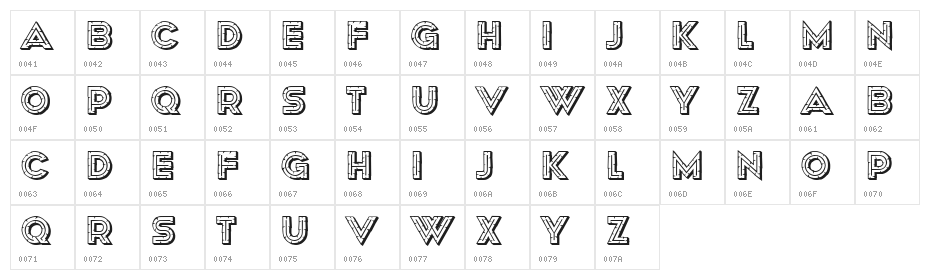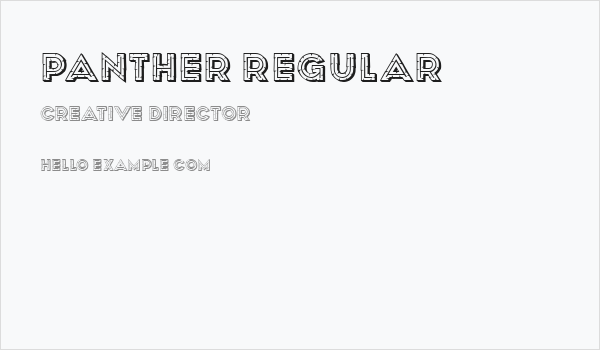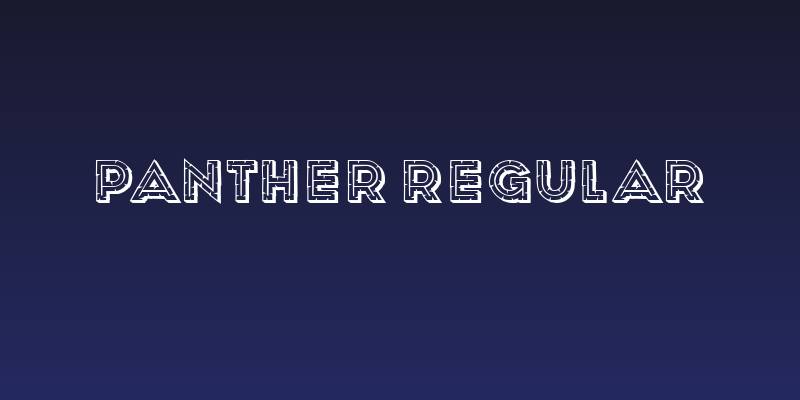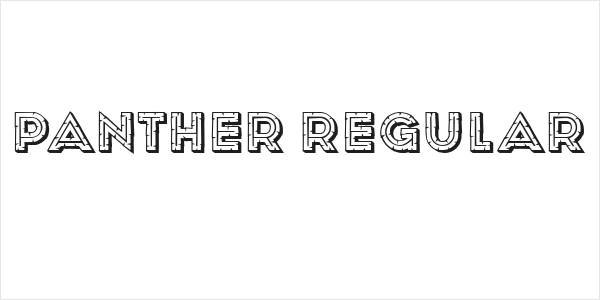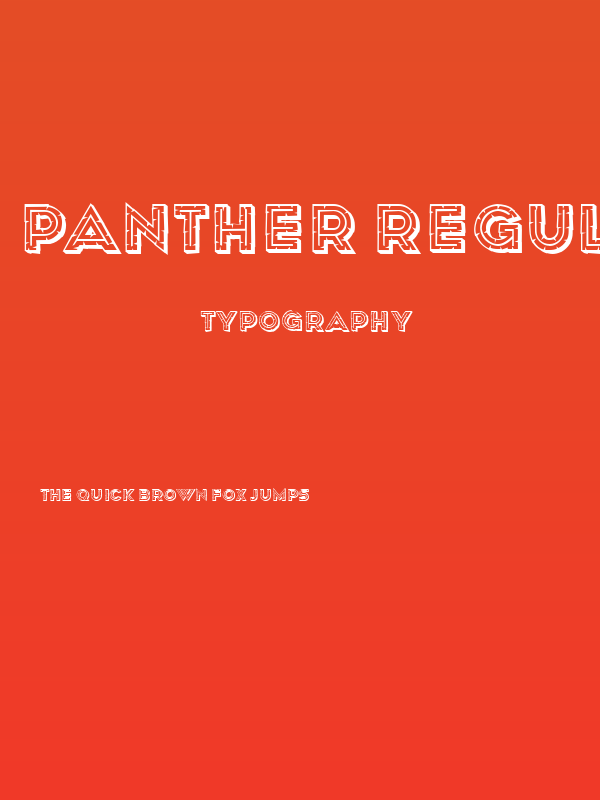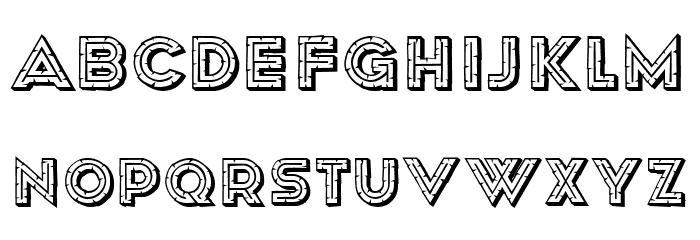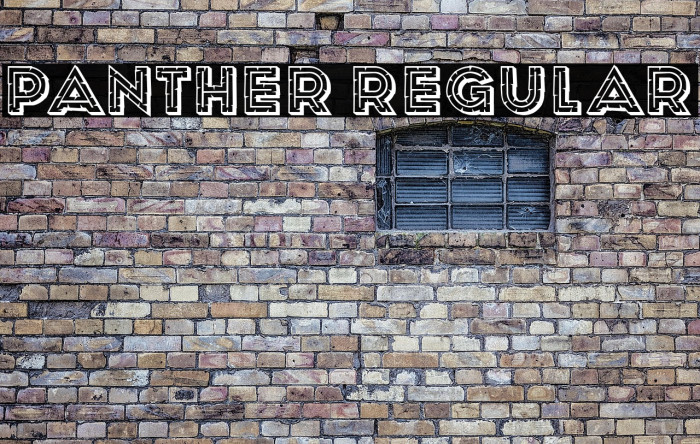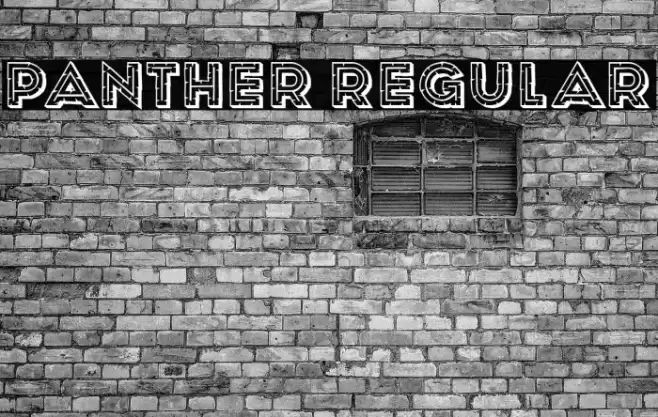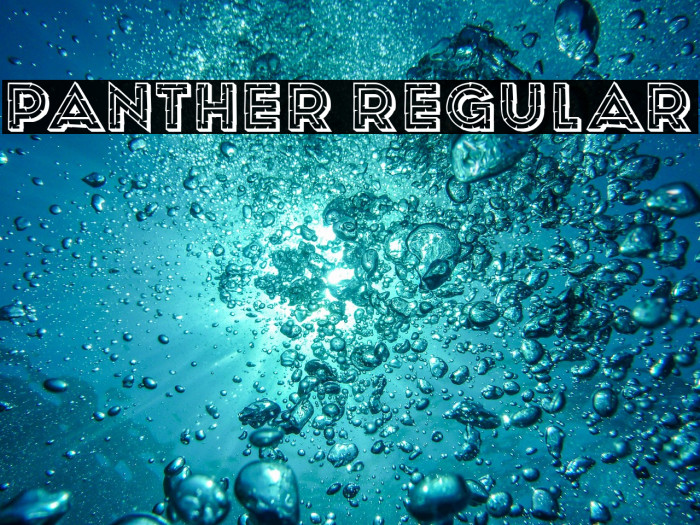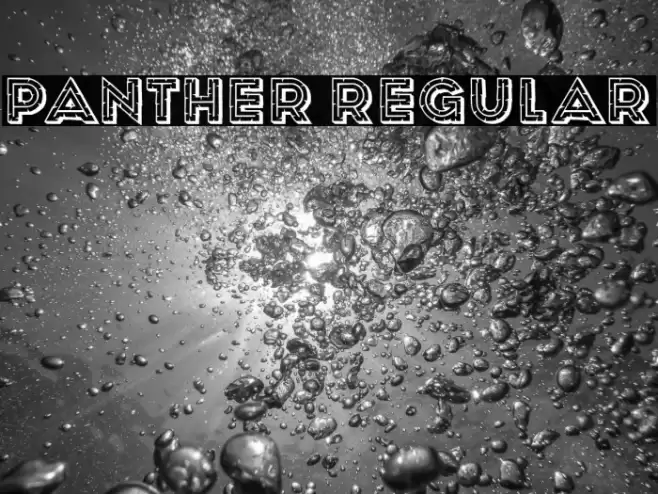
Panther Regular Font
| Proyectos propuestos | Ideal for posters, headlines, logos, and branding materials that require a striking and modern appearance. |